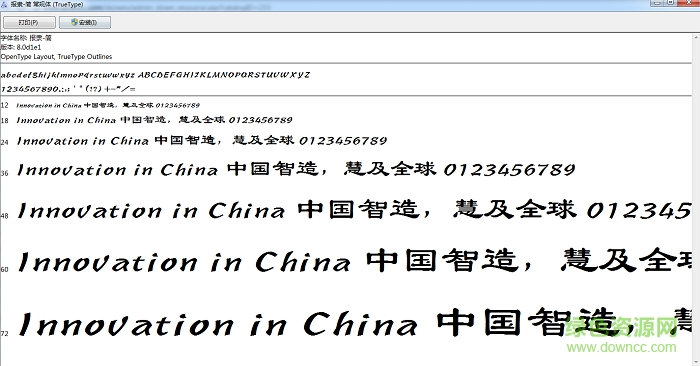
stbaoli sc regular字體是一款典雅莊重的隸書字體,字體結(jié)構(gòu)平穩(wěn),筆畫空隙均勻,整體有一種凝重的氣度,用途十分廣泛,喜歡的朋友快來下載吧!
【起筆蠶頭收筆雁尾】
這是隸書用筆上的典型特征,特別是隸字中的主筆橫、捺畫幾乎都用此法。所謂“起筆蠶頭”,即在起筆藏(逆)鋒的用筆過程中,同時(shí)將起筆過程所形成的筆畫外形寫成一種近似蠶頭的形狀?!笆展P雁尾”,即在收筆處按筆后向上方斜向挑筆出鋒。
【強(qiáng)化提按粗細(xì)變化】
寫篆書時(shí)用筆的縱向提按要求不現(xiàn)痕跡,而隸書則有意強(qiáng)調(diào)提按動(dòng)作,形成筆畫軌跡顯著的粗細(xì)、轉(zhuǎn)承變化,起、行、收用筆的三過程都有了明確的體現(xiàn)。這與后來的楷書已很相近。
【化圓為方化弧為直】
這是隸書簡化篆書的兩條基本路子。不過如果不了解篆書的圓,就不易掌握好隸書的方。因?yàn)殡`筆中的直畫或方折,還無不包藏著篆字的弧勢,所以隸筆的直往往有明顯的波動(dòng)性,富于生命力。實(shí)際上隸書的筆意,是建立在筆畫運(yùn)動(dòng)方式基礎(chǔ)上的。